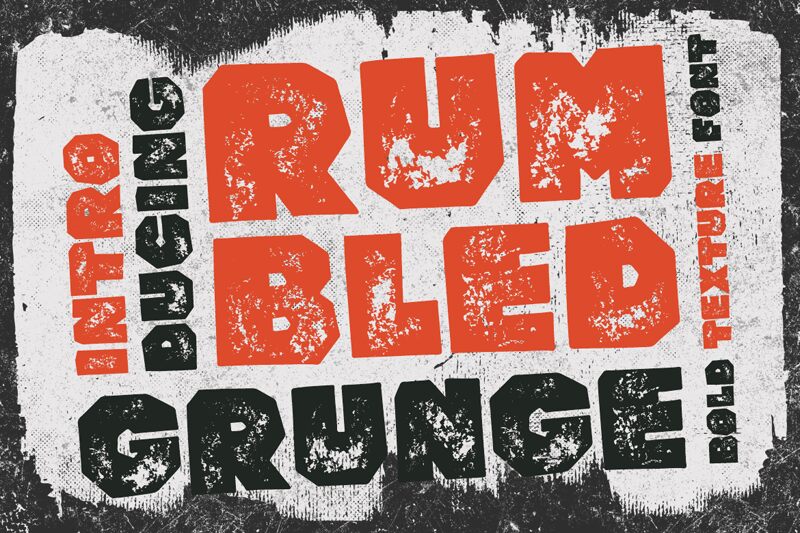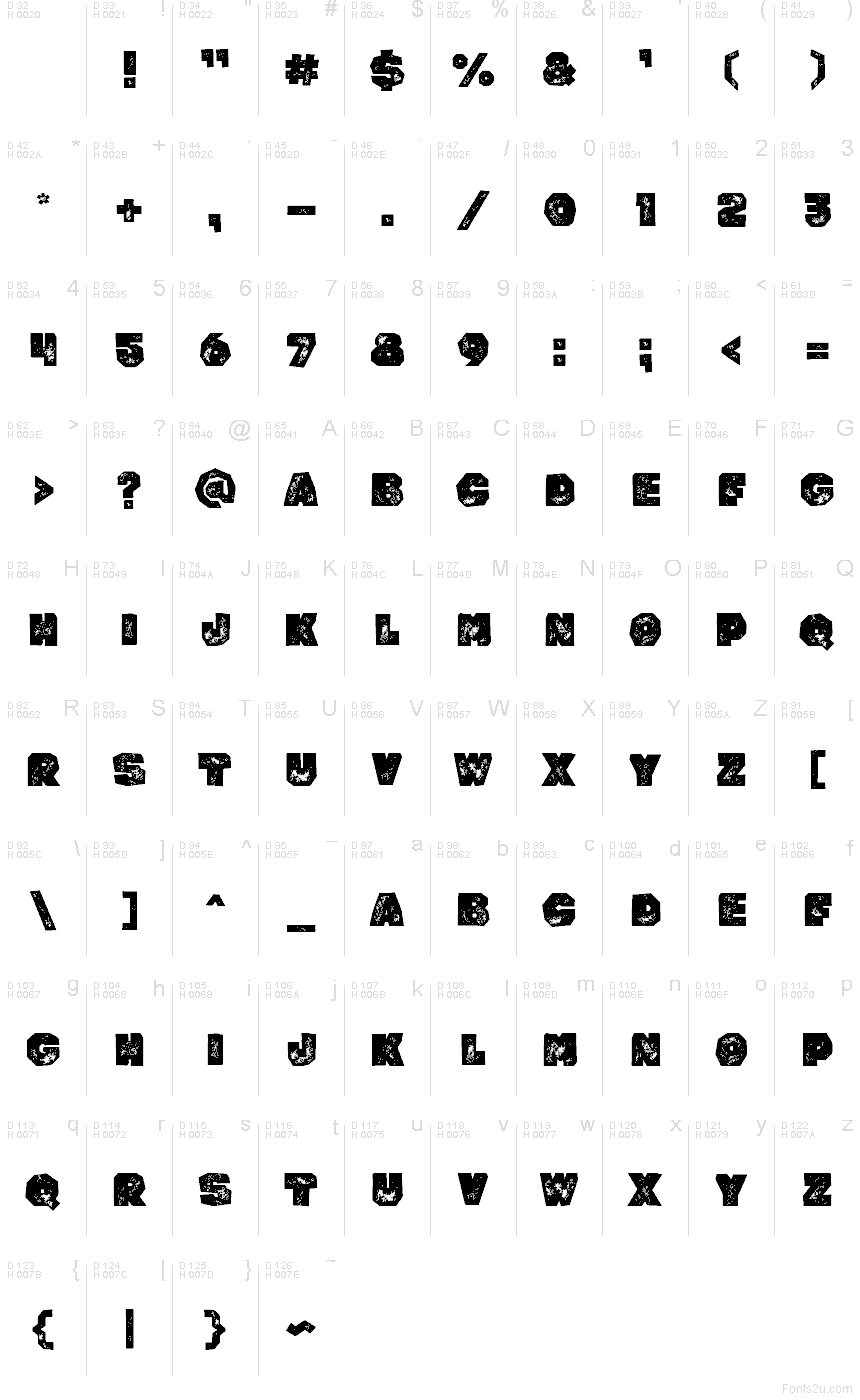
Rumbled Grunge di Shanaf Studio è un font display grunge gratuito e eroso, caratterizzato da maiuscole tozze e squadrate che sembrano scheggiate, prive d'inchiostro e consumate da un uso intenso. Le lettere sembrano ritagliate da forme pesanti e poi graffiate; le imperfezioni puntinate e i bordi irregolari conferiscono all'intero carattere un'estetica urbana e usurata, perfetta per i poster di strada.
È ideale per flyer musicali, grafiche da skateboard, titoli di videogiochi, copertine di fanzine e loghi dallo stile vissuto, dove una finitura pulita risulterebbe troppo formale. Trattandosi di un font gratuito, funziona bene anche per titoli brevi, monogrammi e capilettera, poiché la texture consumata è integrata direttamente nelle lettere e non sovrapposta.